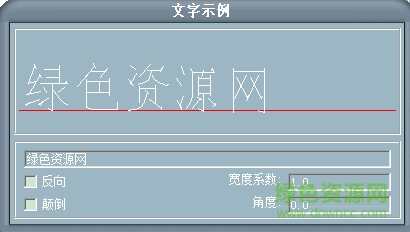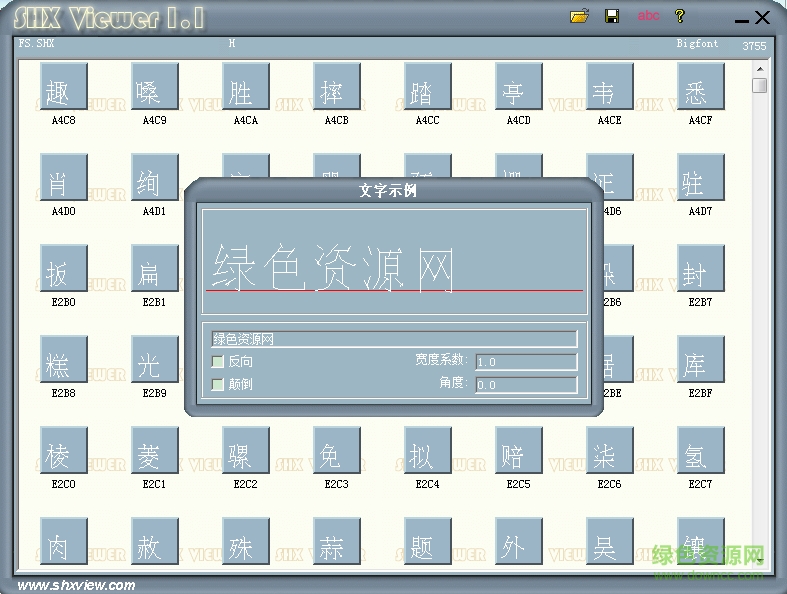
fs.shx字體是一款非常實(shí)用的cad字體,這款字體有著簡潔流暢的字形和線條,廣泛應(yīng)用于cad設(shè)計(jì)中,喜歡這款字體的朋友歡迎來綠色資源網(wǎng)下載使用。
shx文件在CAD里叫形文件,它分為兩種:字體文件和符號形文件;字體文件又分兩種,可以叫做小字體和大字體。
小字體里面只包含一些單字節(jié)(在輸入法里稱為半角)的數(shù)字、字母和符號 ,在文字樣式的左側(cè)列表中列出的都是小字體文件,如果文字樣式要使用CAD字體,首先必須選擇一種小字體。
大字體是針對中文、韓文、日文等雙字節(jié)(全角)文字定制的字體文件。 在文字樣式對話框中必須勾選“ 使用大字體 ”,才能在右側(cè)列表中選擇大字體文件。由于中文、日文的字符比較多,而且每個(gè)字符的定義都比較復(fù)雜,這類文件通常比較大,從幾百K到幾MB不等?!?/p>